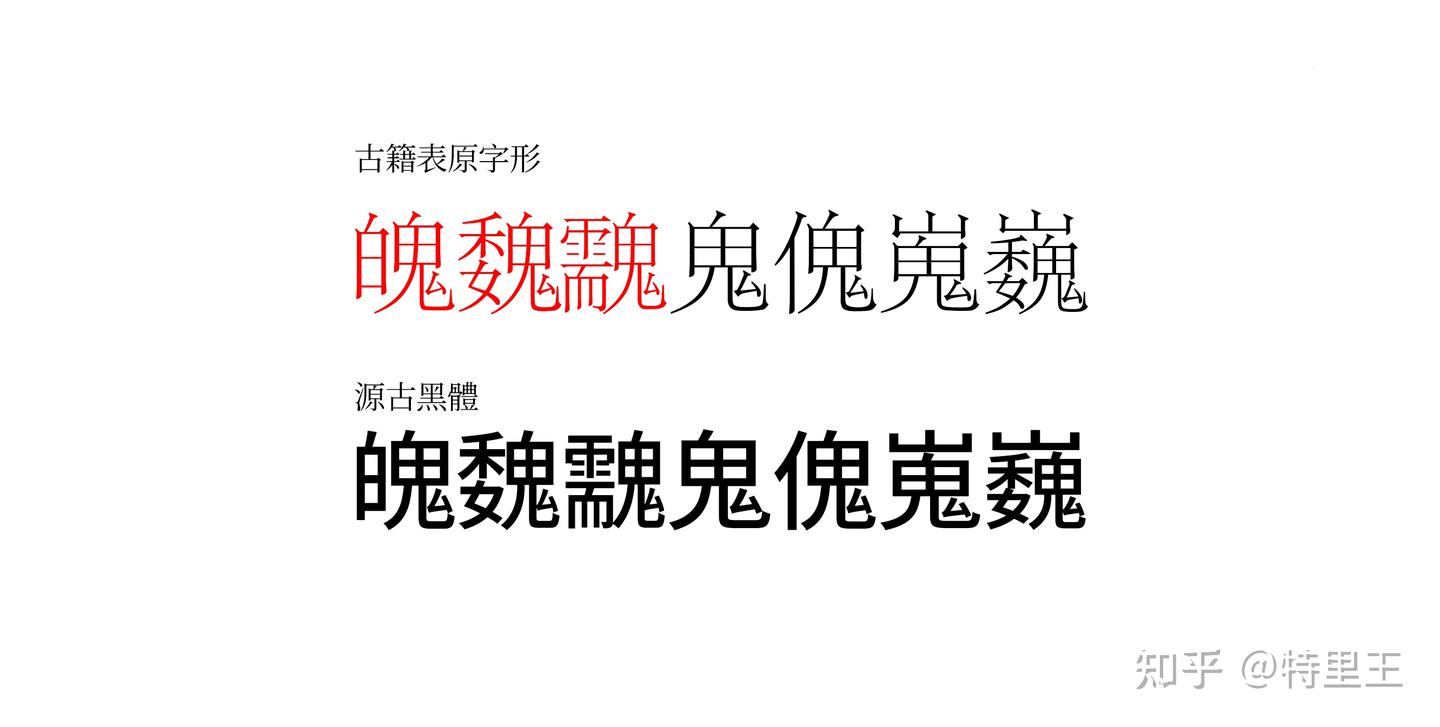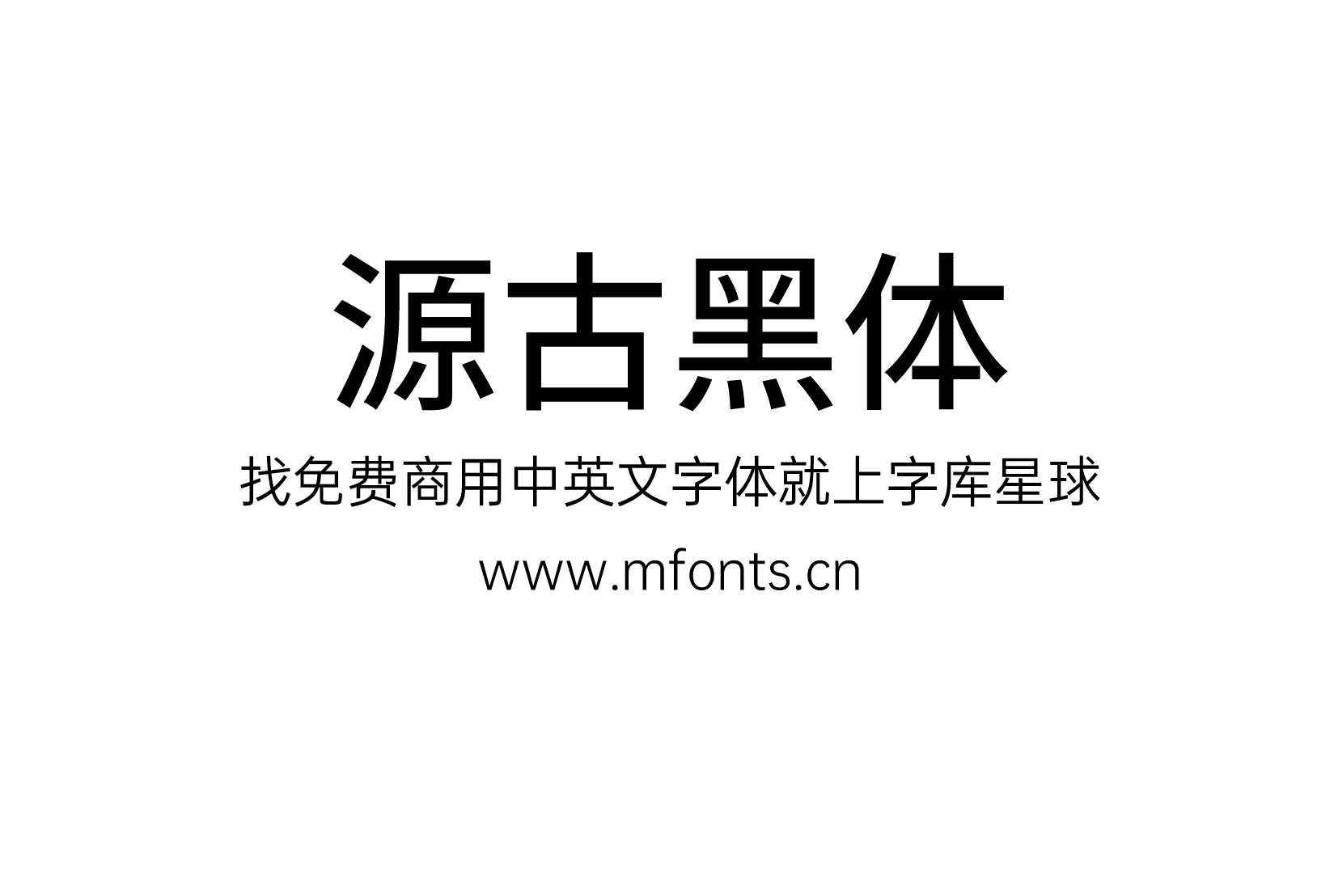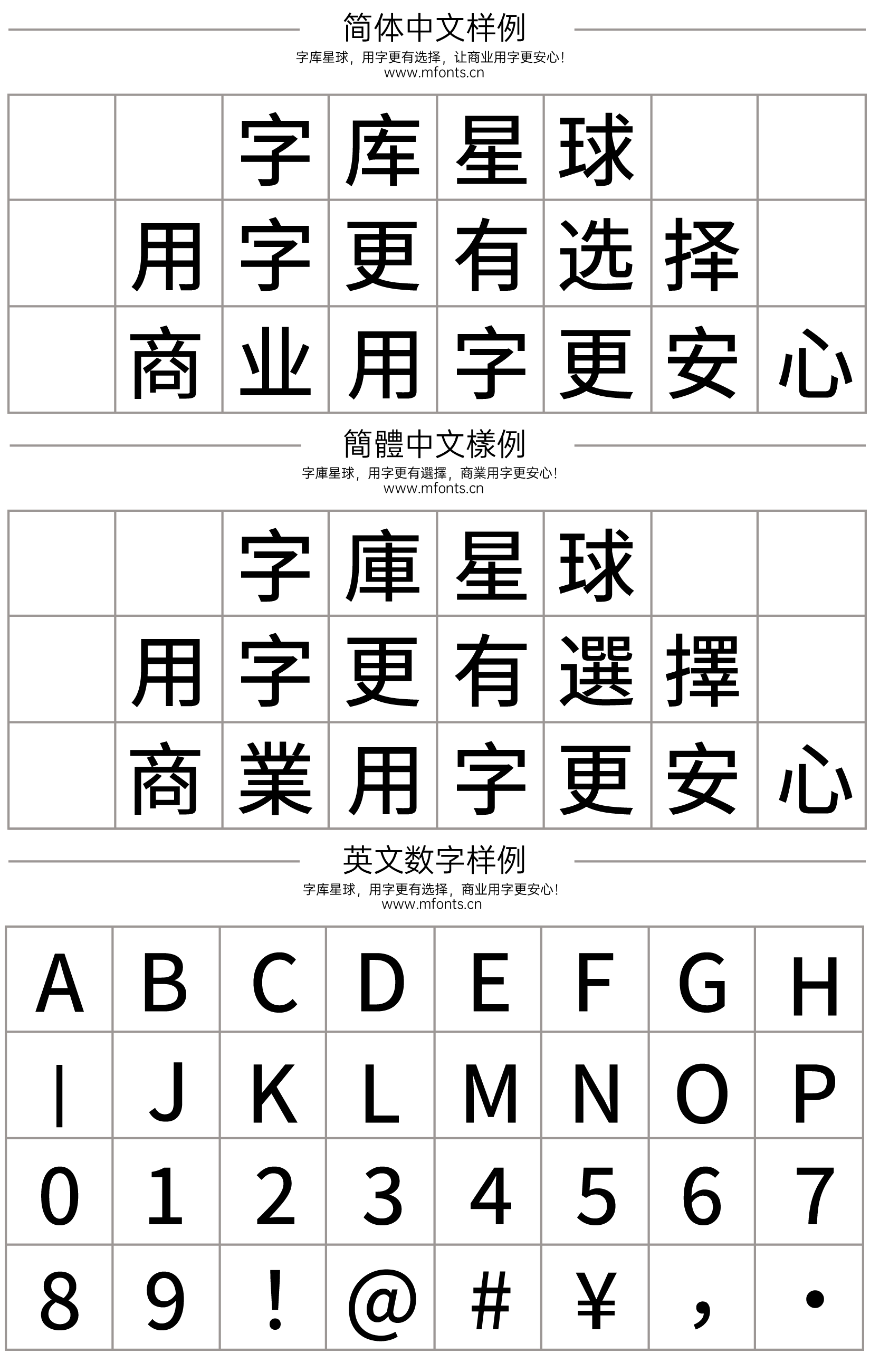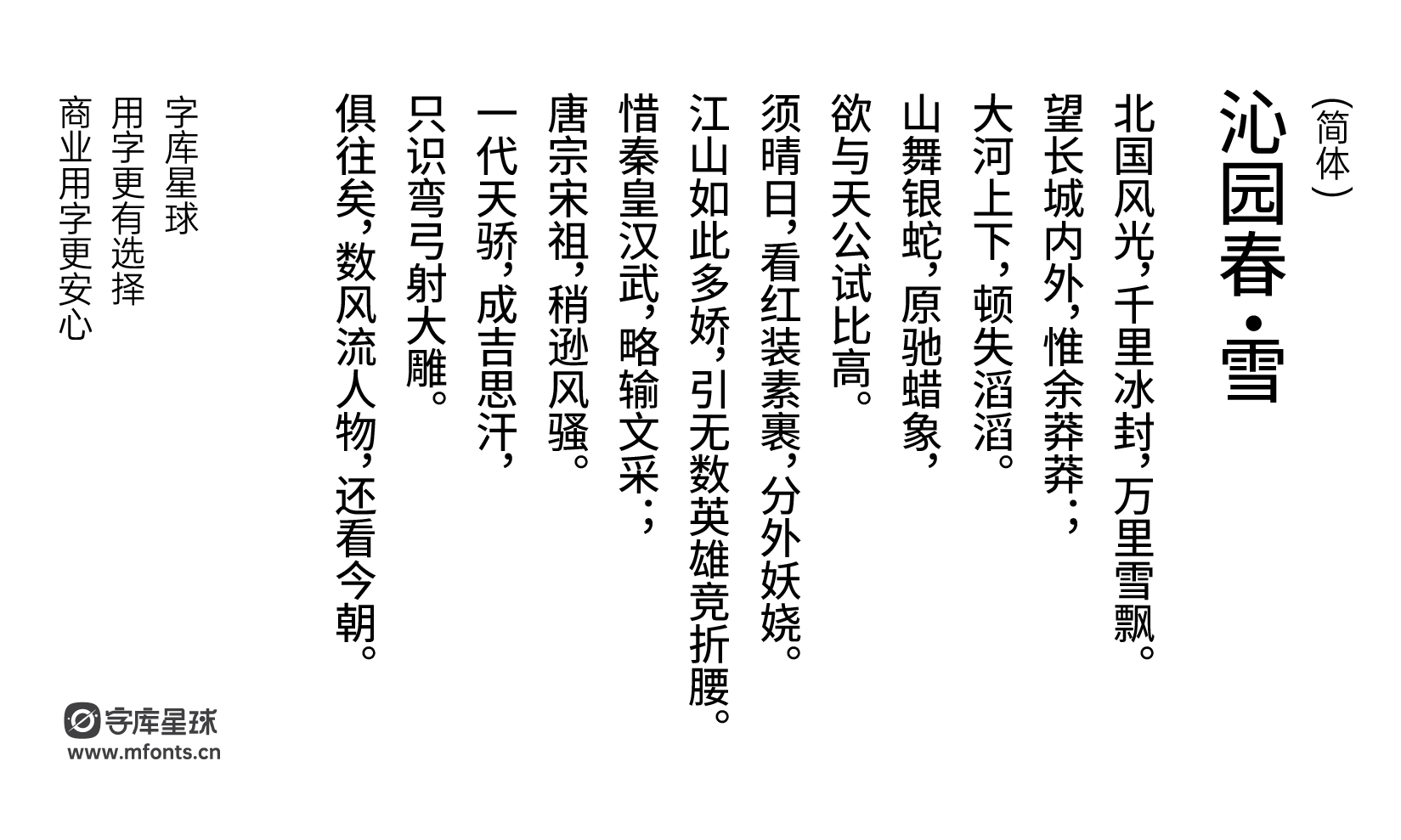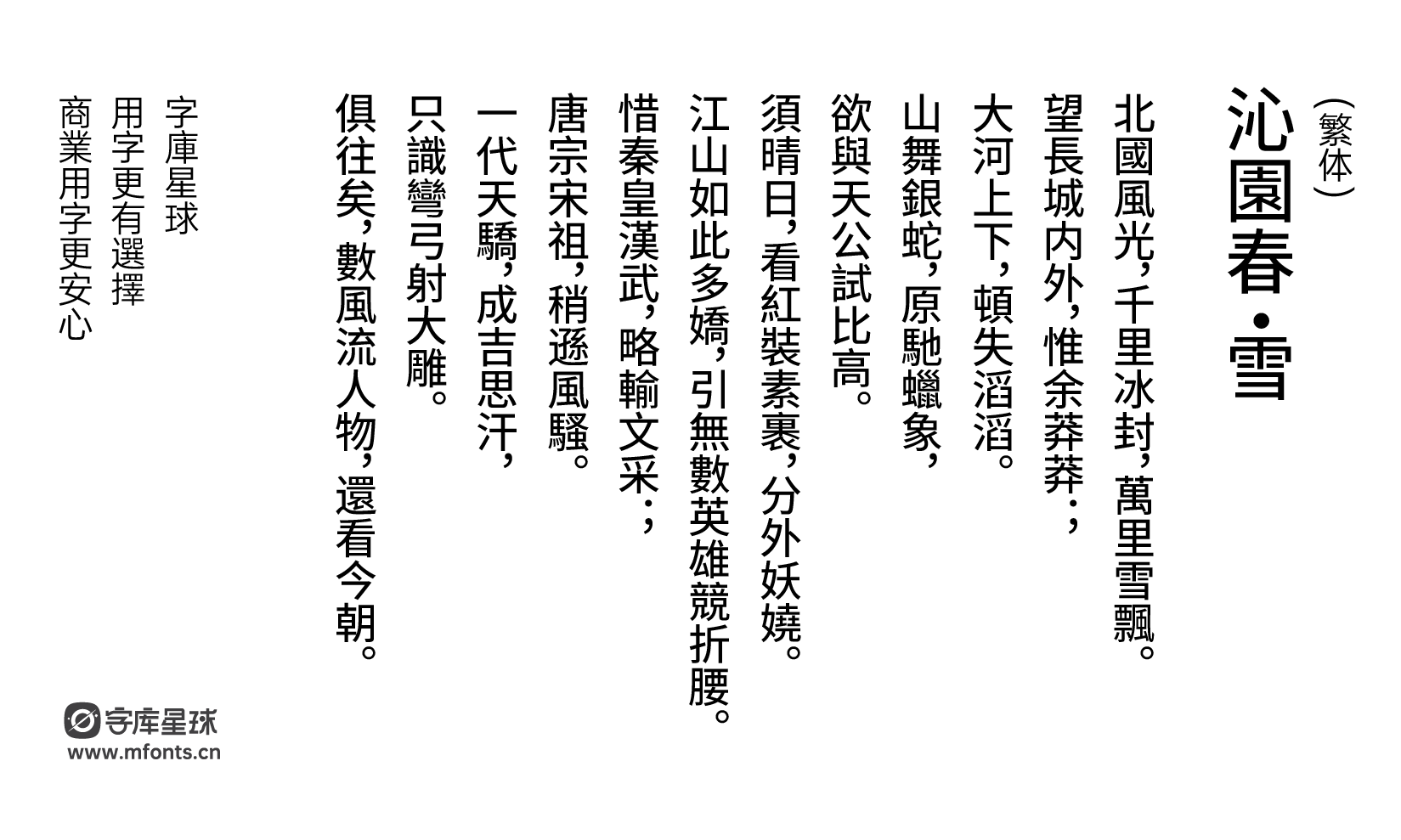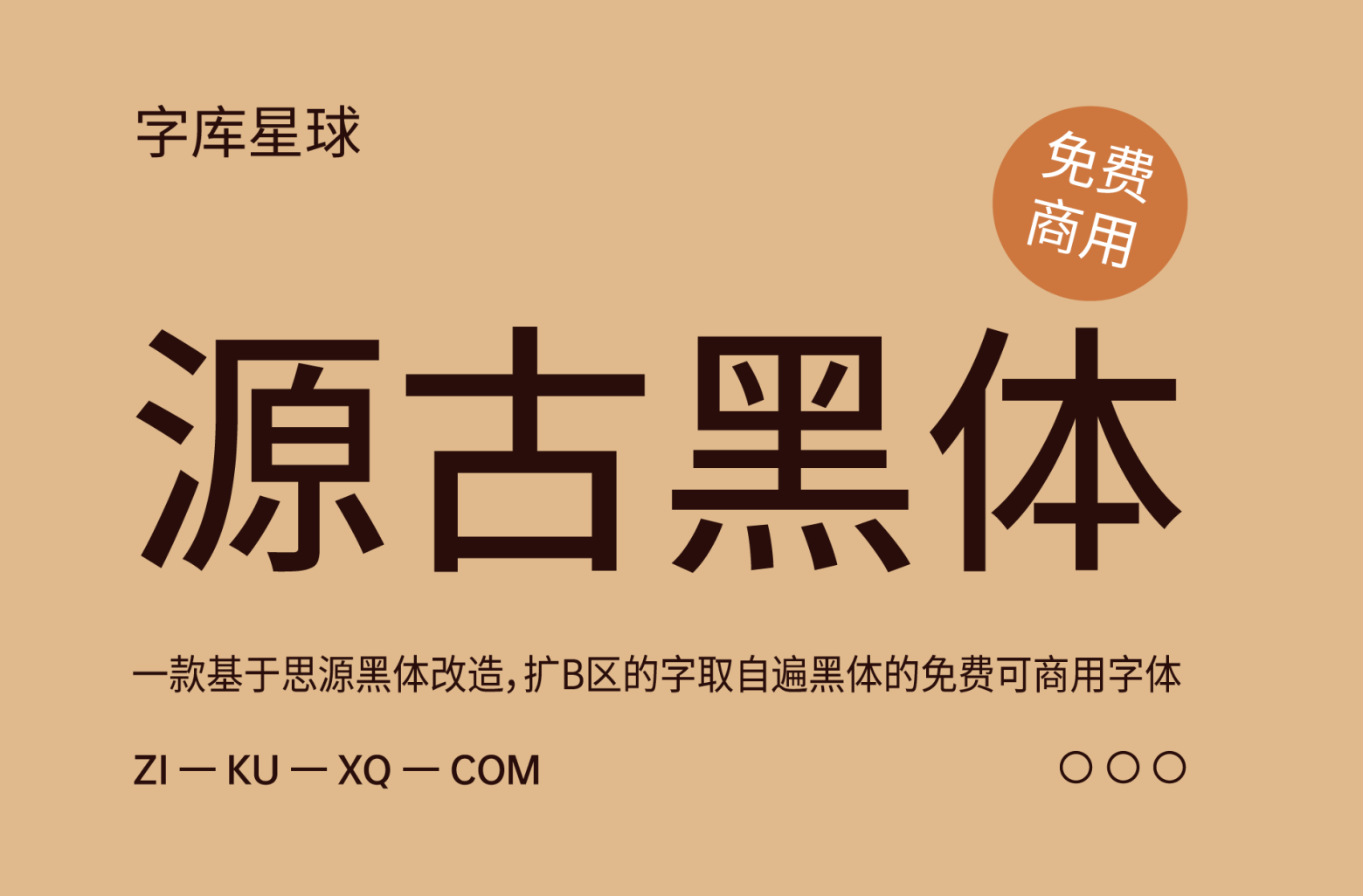
源古黑体
源古黑体是一款基于思源黑体改造,扩B区的字取自遍黑体的免费可商用字体。
源古黑体
得益于思源丰富的地区字形,拆拆凑凑很方便就可以改出一个古籍表版本。而关于那些部件不统一的字,我有选择性地擅自进行了统一。
然后黑体和宋体各提供了两个版本,一个是仅包含古籍表表内字的纯古籍表版,一个是把古籍表外的——思源本来有的那些字一股脑放进去的“F”版本(当然这些表外字就没有按古籍表规范修改,保持思源原样)。
源古黑体
各位可以按需选用。日常看书写东西可以用F版,确保不缺字。
如果要作为做字体的参考或者炼丹的底子,就可以用纯古籍表版,以免被表外字误导。
(没错,其实这次弄这俩字体,本来就是作为炼丹工具性质的
除了这俩思源改,我的竹音仿宋和东乡明朝还在缓慢制作中,都是优先基于古籍表的构型规范做的。单独的京华老宋体古籍表版本正在调试中,后续会择日放出(坑+1)
除了这些“鱼”,我还准备了一些“渔”:我把我做字体时用到的、总结的各种字表都放在了包里。各位做字同仁可对照这些表,把自己的国标字体改造成古籍表标准。(后面我可能也会专门开一个文章来写下这俩具体的区别。(坑又+1)